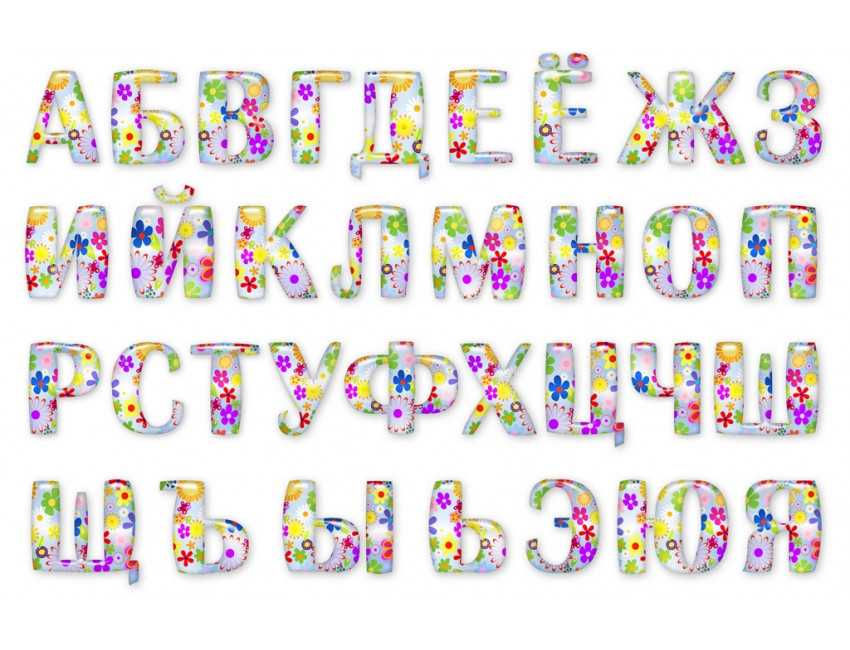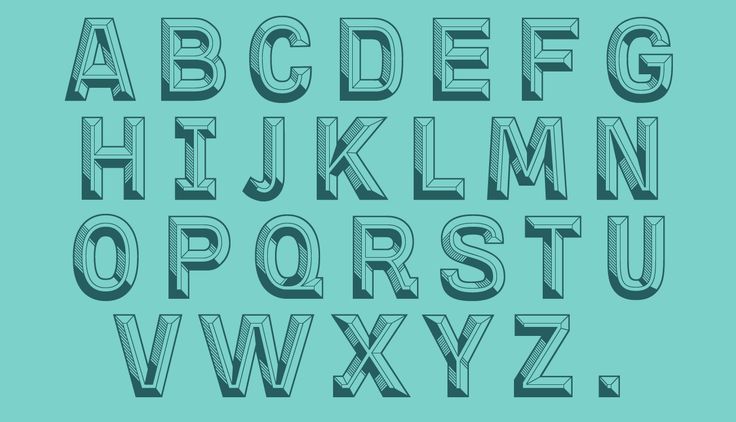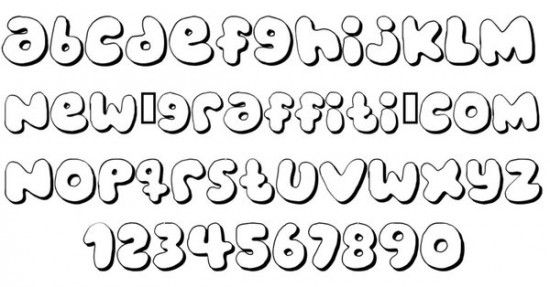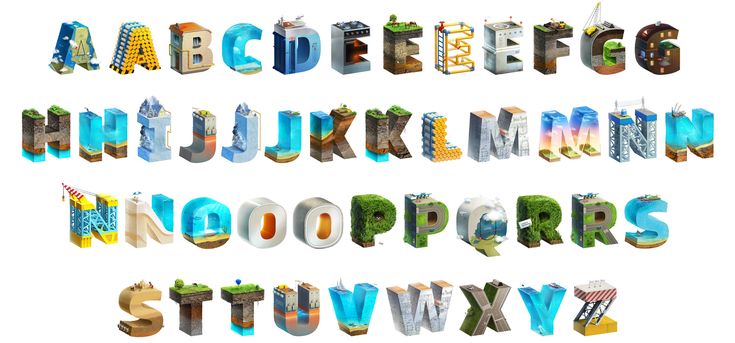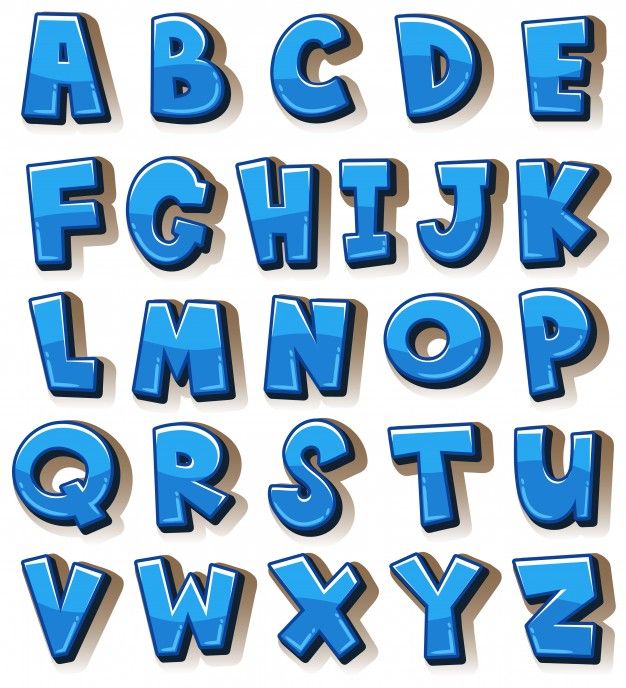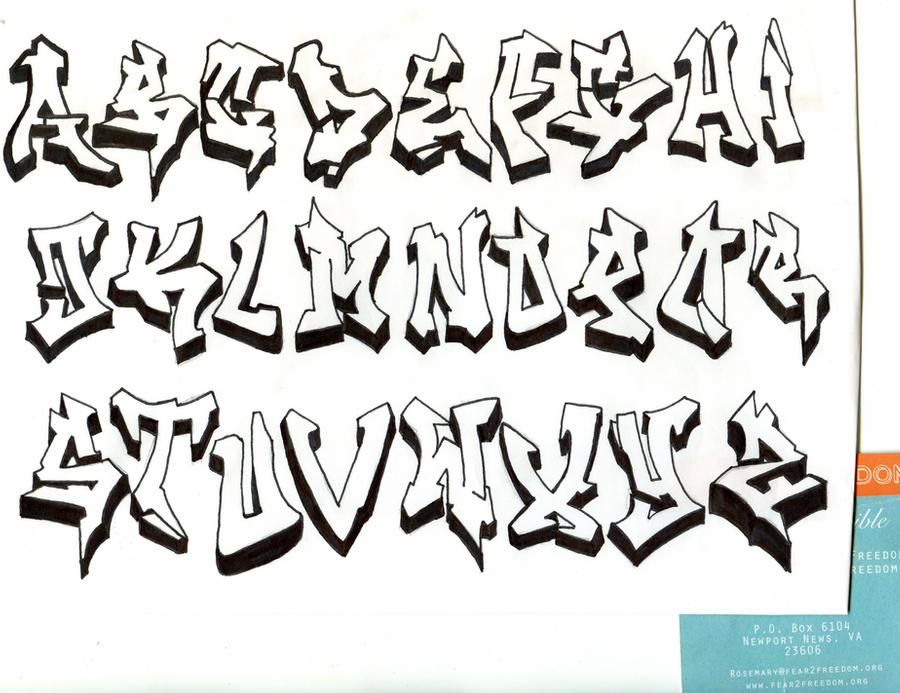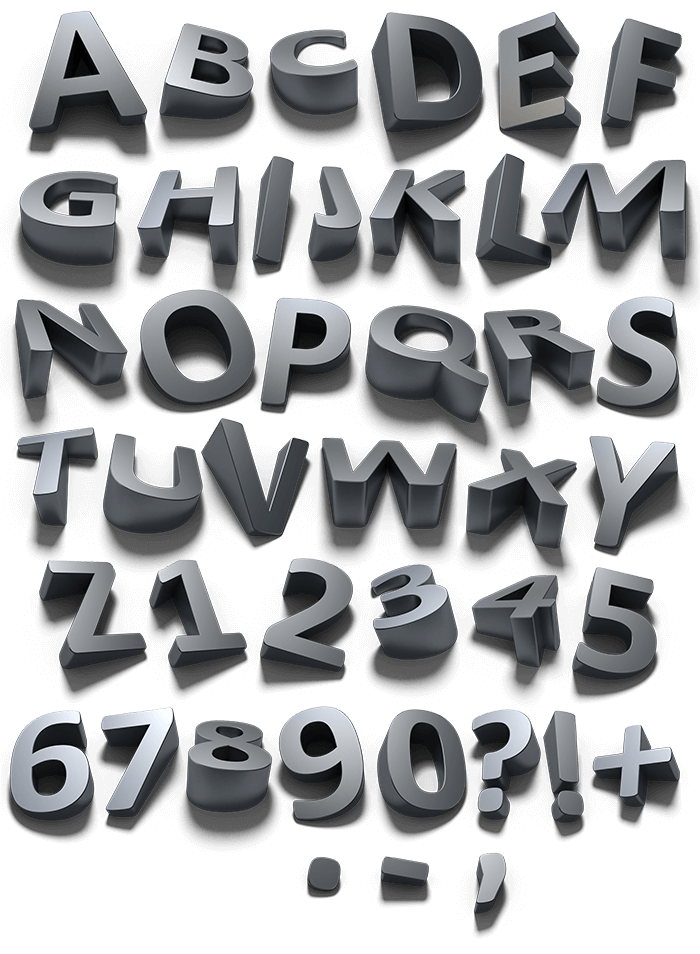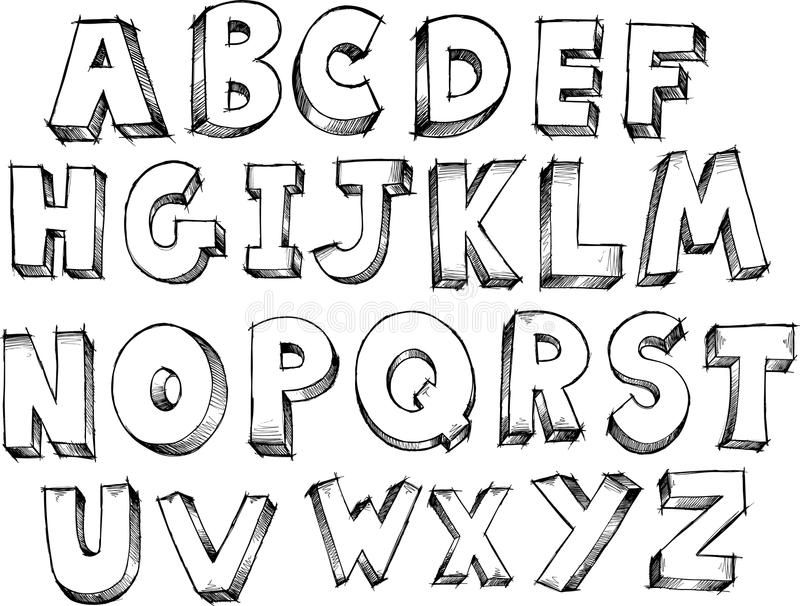
Шрифт объемный — 94 фото
Объемный шрифт для превью
Необычные дизайнерские шрифты
Объемные постеры
Геометрический объемный шрифт
Объемный шрифт из бумаги
Объемные буквы
Объемный шрифт на белую доску
Дизайнерские шрифты
Граффити шрифты
Объемная шрифтовая композиция
Шрифты цветные объемные
Современные шрифты
2d и 3d шрифты
Ретро шрифт кириллица
Дизайнерские надписи
Объем алфавита
Креативные шрифты
Объемный шрифт
Синие английские буквы
Дизайнерские буквы
Объемная типографика
Трехмерные шрифты
Шрифты дизайнерские объемные
Объемные деревянные буквы алфавит
Металлический объемный шрифт
Необычная типографика
Объемные буквы карандашом
Интересные шрифты
Красивый объемный шрифт
Шрифты английских букв современные
Граффити бабл
Дизайнерские шрифты
Разные стили граффити
Объемный шрифт
Плакат с объемными буквами
Объемный шрифт кириллица
Композиция из объемных букв
Леттеринг объемные буквы
Типографика тренды 2021
Золотой шрифт
Объемные буквы граффити
Граффити алфавит русский
Стильные буквы
Красивые объемные буквы карандашом
Шрифты в стиле бабл
Граффити буквы русские
Красивые буквы русского алфавита
Необычные объемные буквы
Граффити шрифты
Буквы из газетных вырезок
Объемный шрифт
Вырезанные буквы
Шрифт лофт
Трехмерные шрифты
Объемные буквы в перспективе
Стиль шрифта бабл гам
Граффити шрифты цифры
Шрифты для рисования
Объемные английские буквы
Граффити в стиле бабл
Красивый алфавит объемный
Шрифты для скетчей
Сырные буквы шрифт
Буква s граффити
Русский алфавит в стиле ретро
Объемная шрифтовая композиция
Пиксельный 3d шрифт
Леттеринг шрифты объемные
Ледяные буквы
Объемный шрифт кириллица
Объемный шрифт для фотошопа
Объемный шрифт для плаката
Шрифт в стиле Стамбула
Объёмный пиксельный шрифт
Объемный алфавит
3d надпись
Красивые объемные английские буквы
Шрифты для мелового Леттеринга
Стили граффити на бумаге
Шрифты для вывесок
Синий объемный шрифт
Дизайнерские шрифты
Красивые объемные буквы карандашом
Объемный графический дизайн
Трафарет шрифта для вырезания
Металлические буквы шрифт
Граффити шрифты
Современные шрифты
Объемный шрифт для фотошопа
Объемная буква в графике
Каллиграфические надписи
2d алфавит